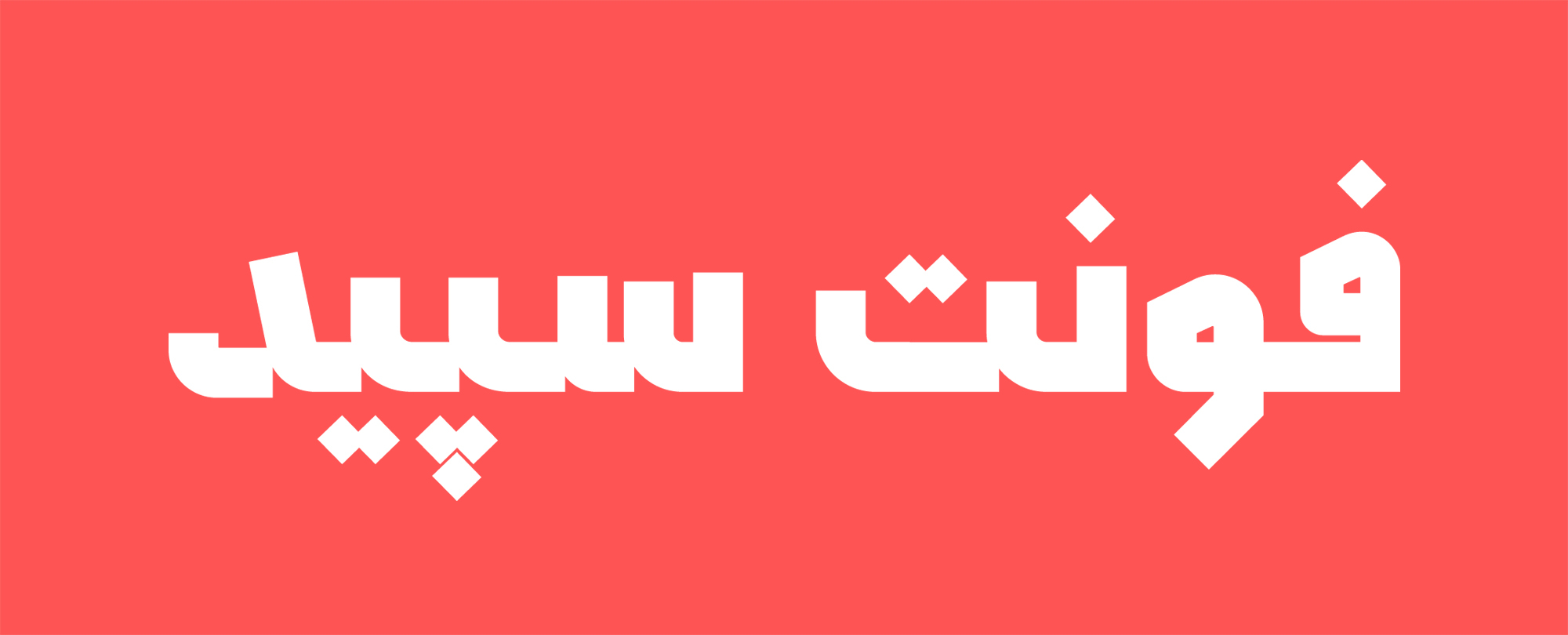
فونت سپید
فونت سپید از دسته فونت‌های هندسی و مونولاین است. طراح با ایجاد شکستگی در فاق‌ها نوعی پیوستگی ویژه ایجاد کرده است که در دیگر فونت‌ها کمتر دیده می‌شود.
با توجه به هندسی بودن، فونت سپید چهرهٔ مدرن و معاصر دارد اما این به معنی جدا شدن از رسم الخط سنتی نیست و طراح سعی کرده است همچنان از خوشنویسی متاثر باشد.
فونت سپید خلاق و جدید است. کاراکترها ساده و در عین حال خاص طراحی شده است و سبک شخصی طراح در این فونت نمایان است.
فونت سپید اگرچه ظاهری محکم و خشک دارد اما پر انرژی و جذاب است.
حروف جایگزین و ترکیبات متعدد در فونت سپید، کمک می‌کند تایپوگرافی‌های نمایشی خاص را طراحی کنید.
سپید مناسب تبلیغات تجاری، صنعتی و طراحی برای شبکه‌های اجتماعی است.
فونت سپید داری هفت وزن و یک استایل اینلاین است. این امکانات کمک می‌کند در عبارت‌های کوتاه نمایشی تا توضیحات از این فونت استفاده کنید.
فونت سپید